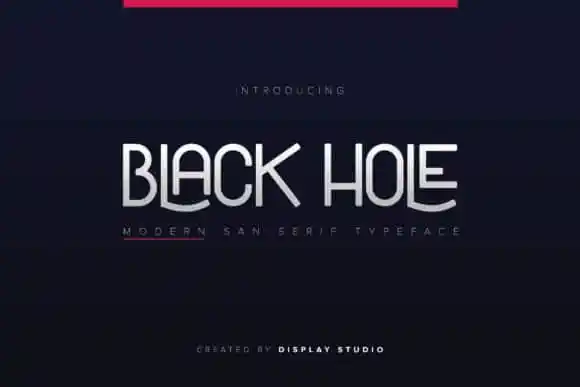
Black Hole Sans Serif Font
A Black Hole Sans Serif Font é uma tipografia sans serif inspirada nos luxuosos aspectos do estilo Art Deco vintage. Esta tipografia ganha vida com sua arranjo elegante e bela disposição de letras, tornando-a perfeita tanto para projetos formais quanto informais. Com seu característica altiva e comprimida, a Black Hole oferece um tratamento refinado em cada letra, o que a torna única. O tema é arrojado, elegante e vintage, mas com uma aposta moderna. A fonte perfeita para projetos de marca de palavra, headlines, títulos, panfletos e outros trabalhos.